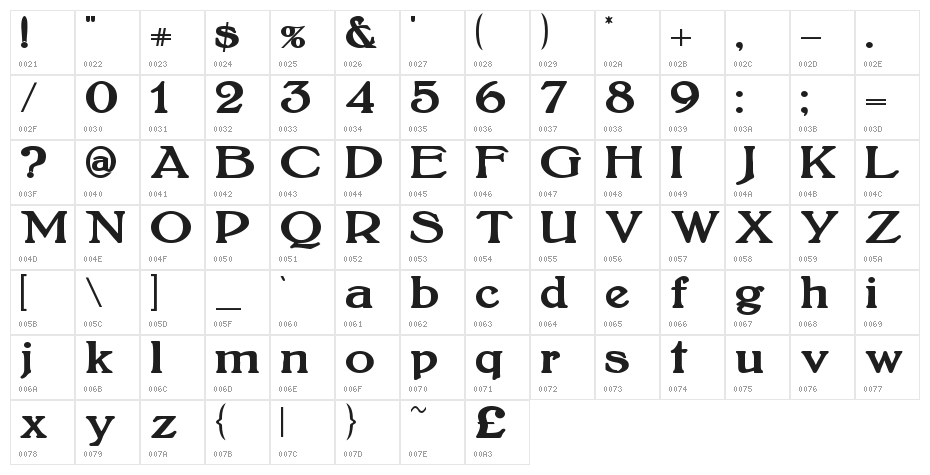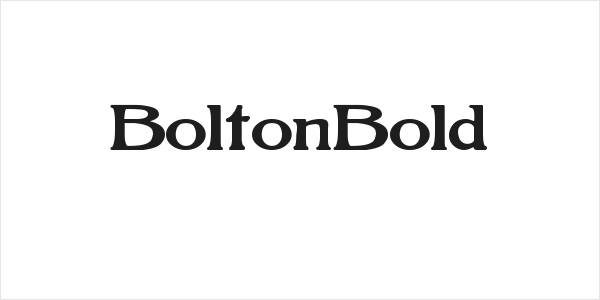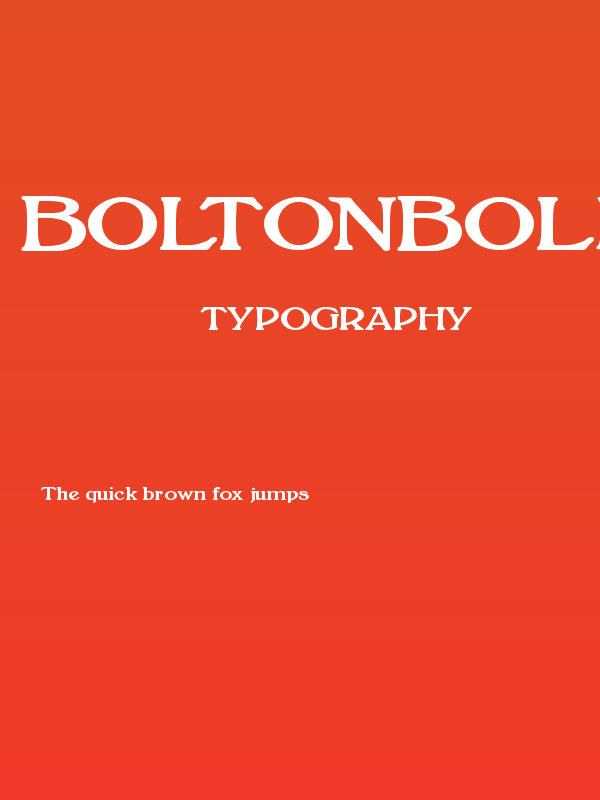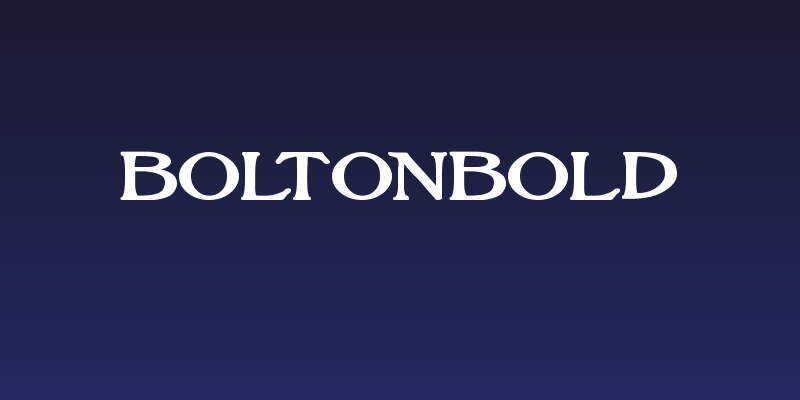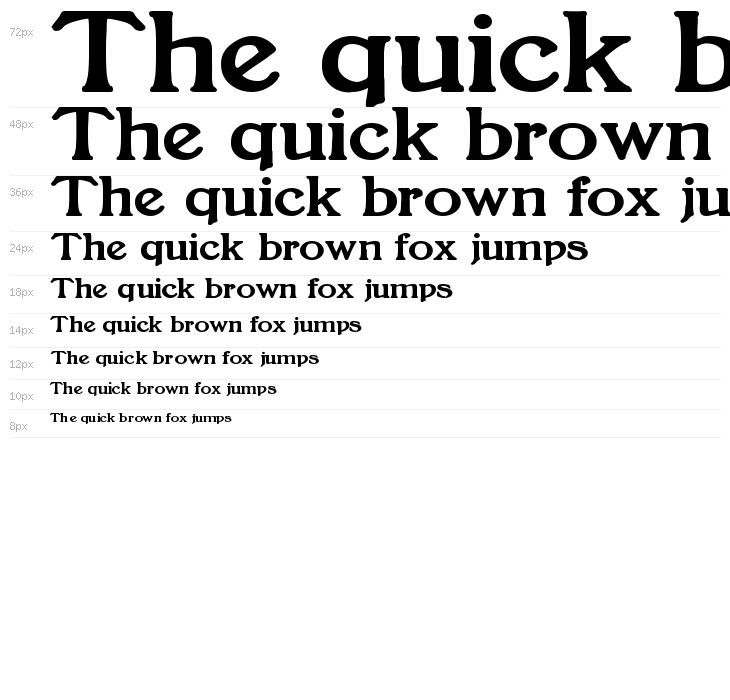
BoltonBold Font
| Stile generale | Modern Vintage |
| Progetti proposti | Ideal for branding, headlines, posters, and any project requiring a bold statement. |